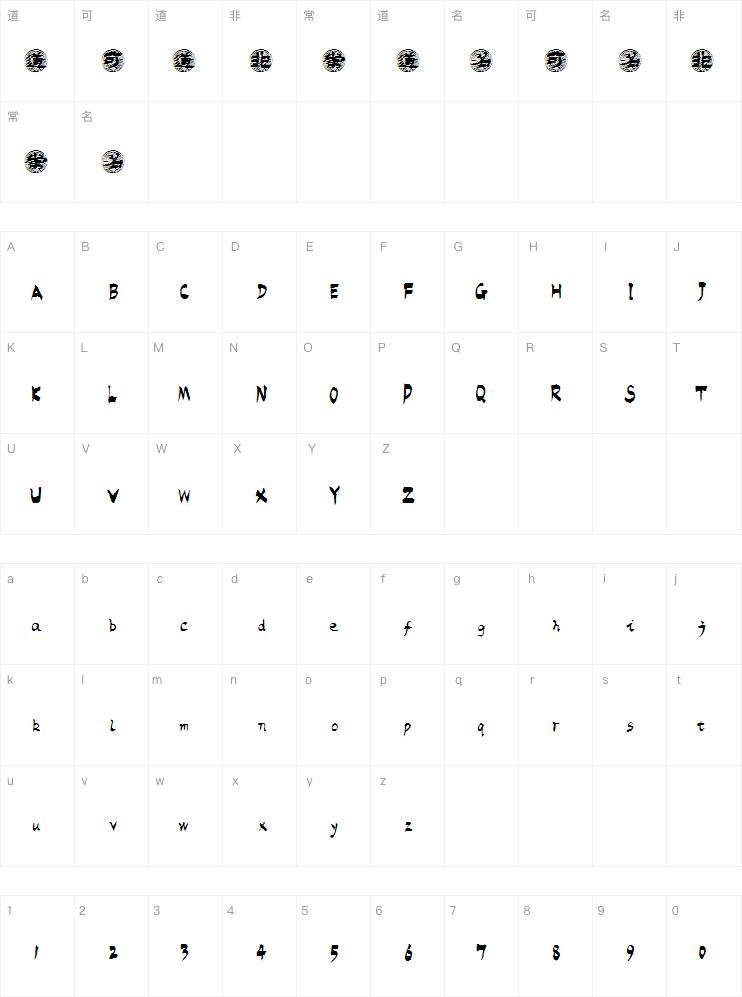
施申财隶书瓦当繁是一款融合汉代隶书风骨与瓦当纹饰美学的繁体书法字体。其字形方正饱满,结构严谨匀称,笔画起落间尽显隶书特有的“蚕头燕尾”波磔韵律,横画粗犷沉稳如篆籀,竖笔挺拔刚健似刀刻,转折处方圆兼济,既有简牍的率真质朴,又带青铜铭文的庄重感。 字体巧妙汲取古代瓦当文字的装饰性特征,在笔画末端与间隙处暗藏浮雕般的凹凸肌理,点画交错间似有金石拓印的斑驳痕迹,整体呈现出浑厚苍劲的金石气息。繁体字形繁而不冗,疏密得当,既保留传统书法的笔墨意趣,又通过现代设计强化视觉张力,适用于古典建筑题字、文化典籍装帧、传统节庆海报等场景,能为画面注入浓郁的汉唐风韵与历史沉淀感。